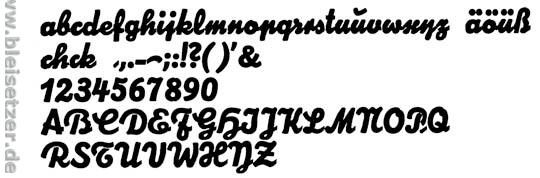
Ganz ohne Kommentar, weil sie mir eben einfielen.
Gerade das Beispiel P&O Ferries zeigt doch sehr deutlich eine Tendenz auf, die sich – beginnend vor etwa 10 Jahren – schon allgemein durchgesetzt hat, nämlich die bildhafte Vierfarbigkeit von Logos. Es ist auf den allermeisten Anwendungen und Produktumsetzungen überhaupt kein Problem, Vierfarbsätze zu drucken, gerade im Verpackungsbereich kommen jede Menge Sonderfarben und weitere Veredlungen wie Prägungen, Lackierung oder Stanzung hinzu.
Ich gebe Schweizerdegen Recht, wenn er meint, ein Logo sollte auch auf der Tasse, dem Freistempler etc. funktionieren. das bedeutet jedoch nicht, dass nicht an anderen Orten sehr viel farbenprächtigere und im Detail wesentlich stärker ausgearbeitete Varianten vorkommen dürften.
Auf der Website von P&O finde ich ich die Flagge gemalt, siehe hier:
Die Tendenz zeigt sich deutlich bei den führenden Marken, wie etwa Langnese, ups, BMW etc. Ich denke, ich brauche die Logos hier nicht hochzuladen, sie dürften allgemein bekannt sein, wie sehen sie alle jeden Tag.
Der Würze halber beziehe ich mich nun ausdrücklich auf Lars Kählers eingstreutes Wort "bildhaft". Genau das war meine Idee, entstanden aus der Lektüre des genannten Artikels über die ungemein unterschätzte Wirkung von Bildern.
Auch, wenn ich nun lese, daß diese Idee schon seit 10 Jahren als Trend existiert, fühle ich mich vom Grundgedanken her bestätigt. Es wäre doch unklug, solche Erkenntnisse der Wirksamkeit zu ignorieren.
Früher war es in Handschriften üblich, dem gemeinen "u" eine Art Übersetzer mitzugeben, einen kleinen parallelen Strich quer über's "u". Auch zu finden in diversen alten Schriften, hier der Werbeschrift Mammut der Ludwig Wagner AG, Leipig von 1927:
Wenn ich schreibe "Handschriften", dann meine ich das wörtlich. Ich selbst und alle meiner Generation, die ich kenne, verwenden diesen u-Querstrich. Meine jugendlichen Kinder nicht.
Das Versal-U empfinde auch ich als lesbar.
Das BMW-Signet ist ein Bild, es zeigt einen rotierenden Propeller (BMW baute schon lange vor Autos Flugzeugmotoren). Im wesentlichen stimme ich zu, die Beispiele oben sind eher bescheiden, vielleicht mit Ausnahme des Pandas, der gelungen umgesetzt ist sicher auch seinen Zweck erfüllt. Um dem Hund/Pferd recht zu tun: auf den Lastwagen der Firma sieht das Logo erstaunlich gut aus (hier allerdings nicht). Aber im Prinzip finde ich diesen Grad von Abstraktion in Ordnung. Das Eichhörnchen ist eine misslungene Vereinfachung eines Vorgägersignets, das schön war.
Ich glaube nicht, das es an den Gestaltern liegt. Gäbe es eine Nachfrage würden die schon zeichnen lernen, wenn sie es den nicht können. Wollen die Kunden den Bildmarken? Ich denke, je mehr Leute mitentscheiden (je größer also die Firma), um so schwerer wird es, die heute schon exotische Idee eines Signets zu vermitteln.
Ohne das ich mit einem Drucker über die Kosten des Drucks streiten will: ist es nicht so, das für die kleineren Auflagen kleinerer Auflagen und die sehr großen Auflagen die kosten für farbigen Druck kaum mehr ins Gewicht fallen, wenn der Kunde mit einfacher Qualität zufrieden ist, weil ohnehin regulär in CYMK gedruckt wird (ich meine natürlich nicht den Druck in Blei)? Man denke nur an die ganzen Internet-Diskount-Druckereien, auch wenn man deren Erfolge mit guten Gründen bedauern kann.
Interessant, diese Propeller-Geschichte. Das Eichhörnchen gehört zur französischen Caisse d'Epargne (Sparkasse). Ich finde im Augenblick nur die aktuelle Version. Es gab eine ganze Reihe von Stufen über die Jahre. Am Anfang stand wohl eine Satire auf Delacroix "Die Freiheit führt das Volk an" mit écureuil als liberté (die Sparkassen haben in Frankreich in humanistischen Bewegungen ihren Ursprung).
Gäbe es eine Nachfrage würden die schon zeichnen lernen, wenn sie es den nicht können.
Ich bin Grafikdesigner mit besonderem Interesse an den Themen Corporate Design und Typografie.
Ich kann ein bisschen fotografieren, aber wenn ich gute Fotos brauche gehe ich zum Fotografen.
Ich kann ein bisschen schreiben, aber wenn ich gute Texte brauche gehe ich zum Texter.
Ich kann ein bisschen schriftgestalten, aber wenn ich gute Fonts brauche gehe ich zum Schriftgestalter.
Ich kann ein bisschen zeichnen, aber wenn ich gute Zeichnungen brauche gehe ich zum Illustrator.
Ich kenne wenige Grafiker die gute Illustratoren sind und wenige Illustratoren die gutes Grafikdesign machen. Wir sind ja meist keine Wunderwuzis und können nicht alles können. Zwar sollte der Grafiker eine Ahnung vom Zeichnen haben und vom Fotografieren und er sollte auch dem Text nicht gleichgültig gegenüberstehen — aber meist ist es besser wenn er die Spezialdisziplinen den Spezialisten überlässt.
In diesem Sinne halte ich es nicht für tragisch, dass die meisten Grafiker keine Künstler sind (tragisch ist’s nur wenn sie’s glauben zu sein)
Einspruch, Euer Ehren! Das Fax ist ein Urvieh, das braucht nur eine primitive Umsetzung des Logos, quasi eine Sonderform, überall woanders lässt sich Farbe einsetzen. Jederzeit. Tag und Nacht. Tonnenweise.
... ein Warenzeichen, das eigentlich ein Wahrzeichen war.
Das geht doch schon stark in Richtung Wehrzeichen. Hat jedenfalls einen hohen Wiedererkennungswert und lässt Entschlossenheit im Umgang mit Markenrechtsverletzern und Produktpiraten erahnen.